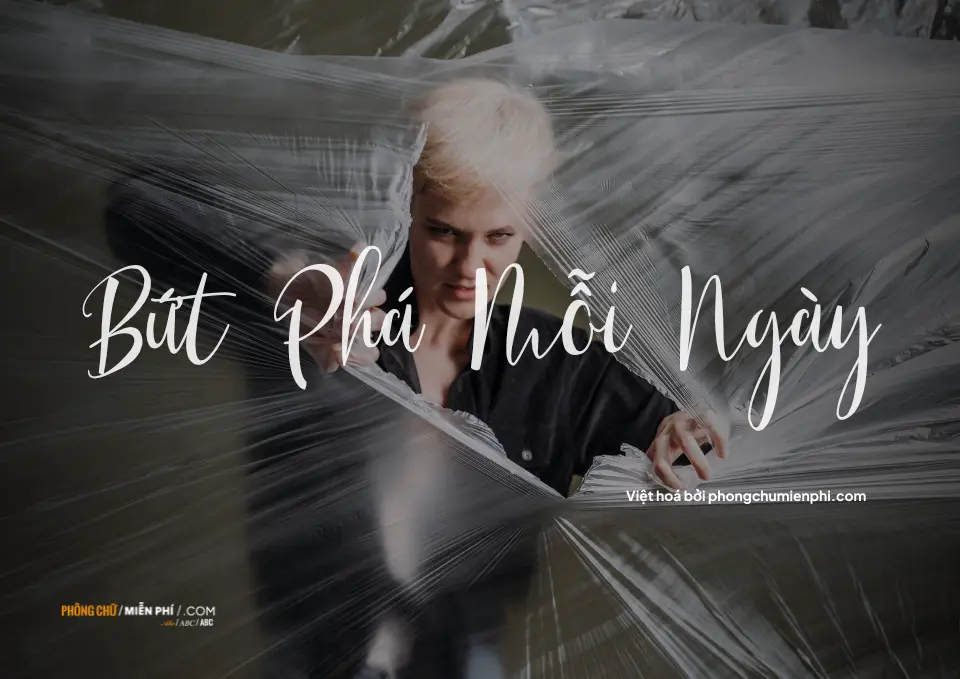
Font Việt hoá PCMP Generating Script
PCMP Generating Script là font chữ viết tay. Đây là font chữ hoàn hảo cho mọi thiết kế thú vị của bạn. Mọi thứ đều được tạo nên từ nét cọ ngộ nghĩnh. Vì vậy, bạn có thể yên tâm rằng chúng sẽ kết hợp hoàn hảo với nhau! Bởi vì chúng tôi đã biên soạn các khoảng cách và ma trận được thiết kế riêng theo nhu cầu của bạn.
PCMP Generating Script hoàn hảo cho các dự án xây dựng thương hiệu, logo, thiết kế đám cưới, bài đăng trên mạng xã hội, quảng cáo, bao bì sản phẩm, thiết kế sản phẩm, nhãn mác, nhiếp ảnh, hình mờ, thiệp mời, văn phòng phẩm và bất kỳ dự án nào.